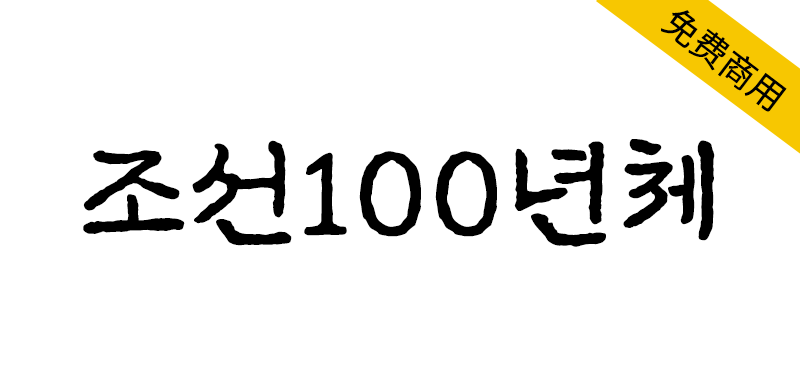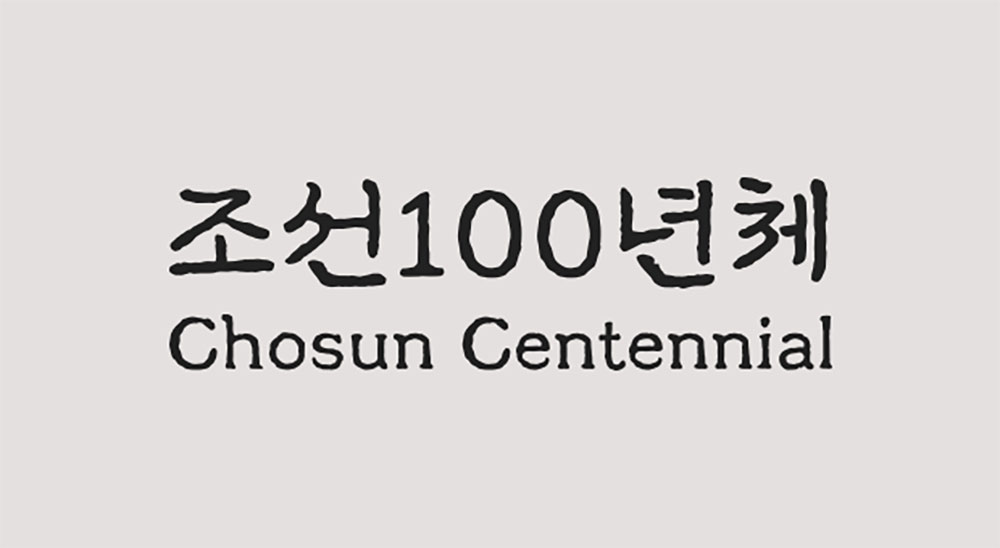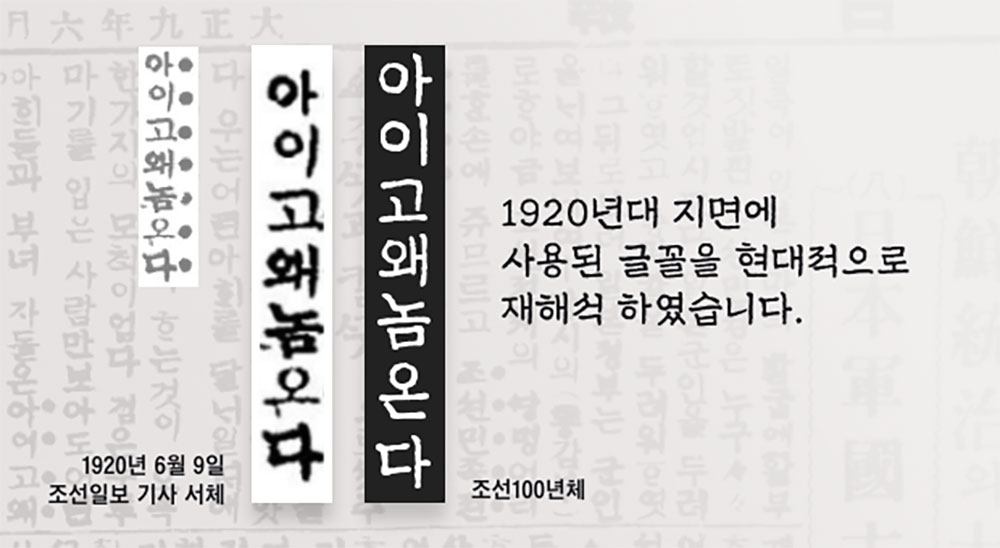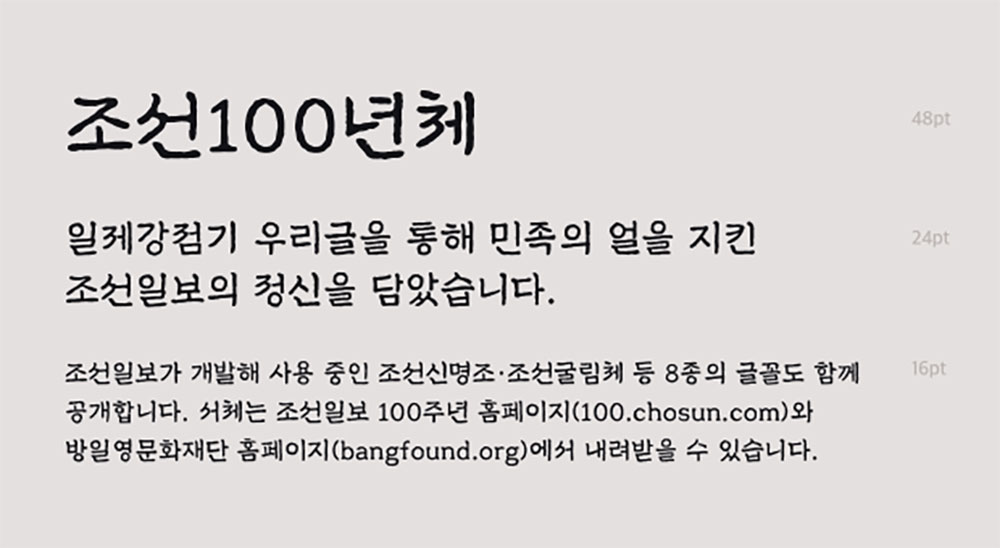
【조선100년체】朝鲜日报1920年代使用的字体的现代修复版
纪念《朝鲜日报》创刊100周年的《朝鲜100年》,我们免费分发“조선100년체”,这是朝鲜日报在1920年代使用的字体的现代修复版。这种字体由方日荣文化基金会开发,体现了《朝鲜日报》的精神,即在日本殖民时期通过朝鲜文字保存了民族精神。
조선일보 창간 100주년 기념 ‘조선100년체’.1920년대 조선일보에서 사용한 글꼴을 현대적으로 복원한 ‘조선100년체’를 무료 배포합니다. 방일영문화재단이 개발한 이 서체는 일제강점기 우리글을 통해 민족의 얼을 지킨 조선일보의 정신을 담았습니다.